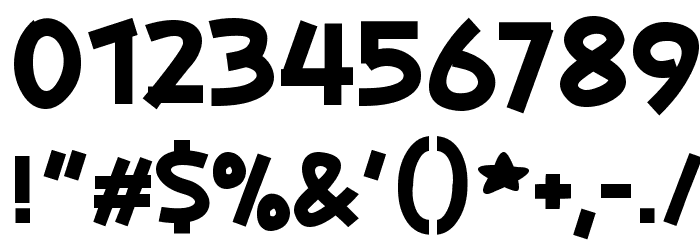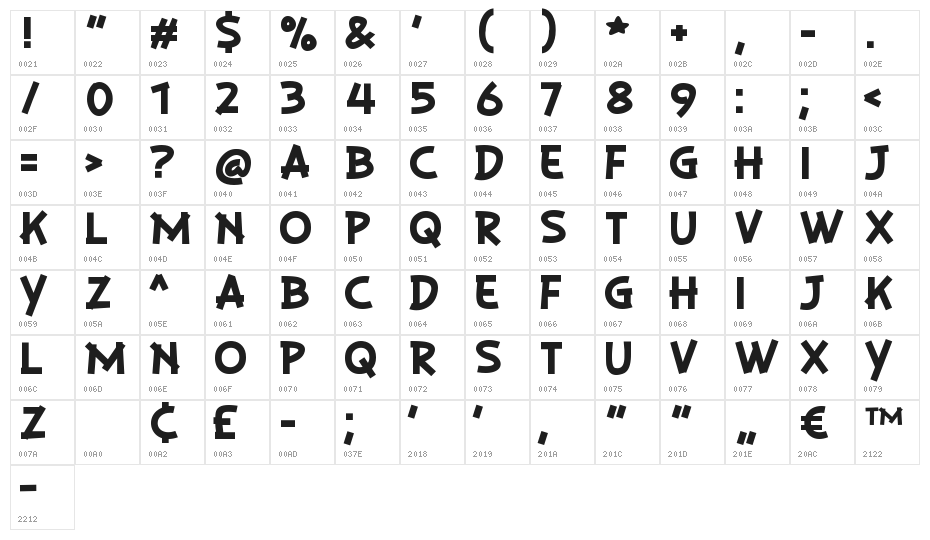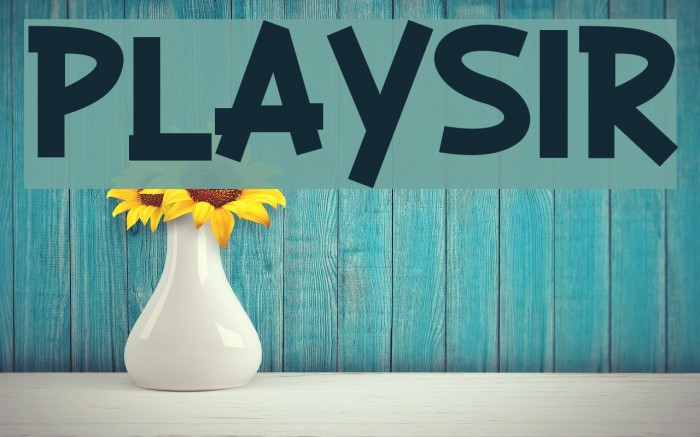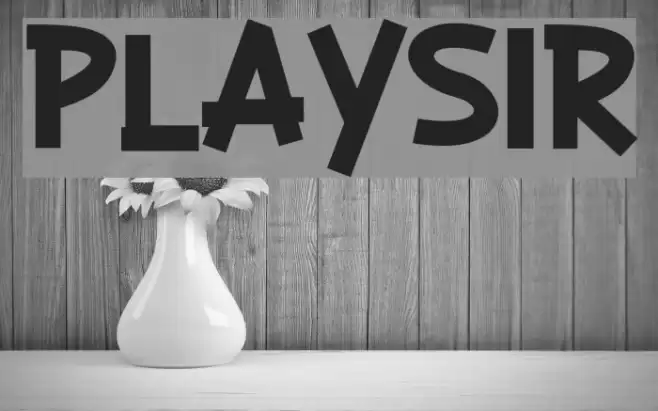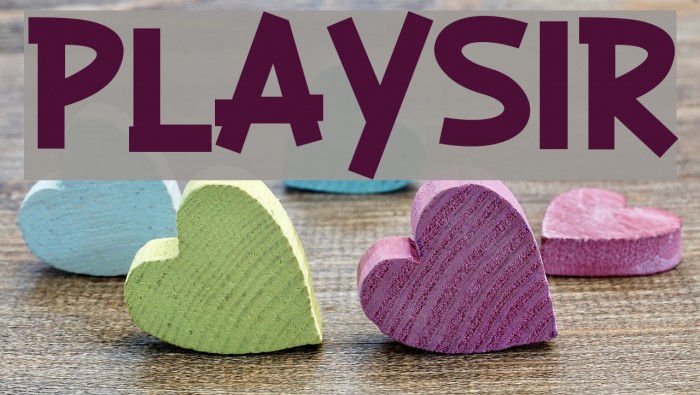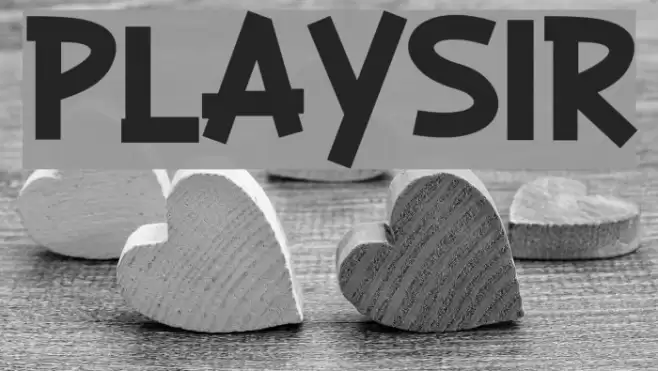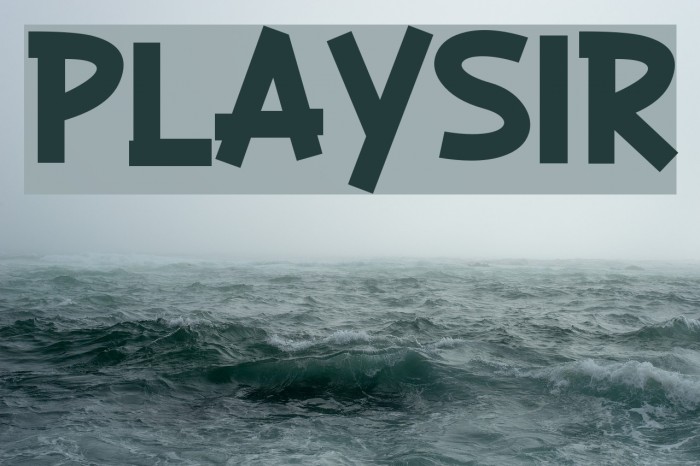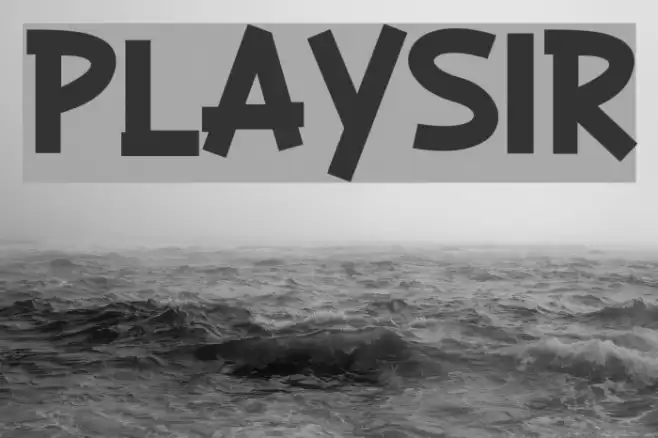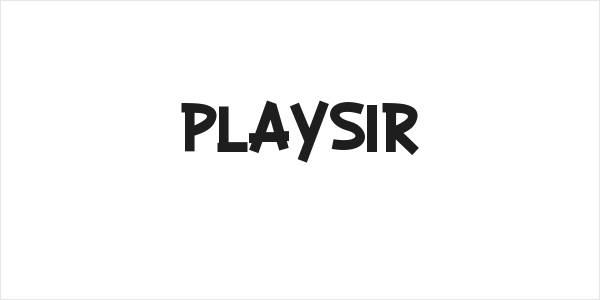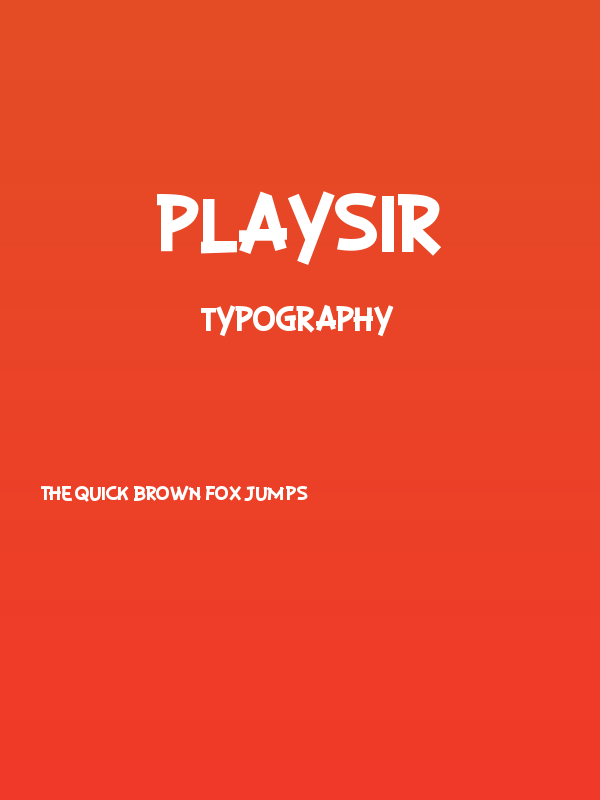
PLAYSIR Font
| Gesamtstil | Playful, Energetic |
| Anwendungsfall | Headlines, Posters, Branding |
| Vorgeschlagene Projekte | Ideal for posters, children's books, comic strips, and branding materials that require a fun and energetic vibe. |